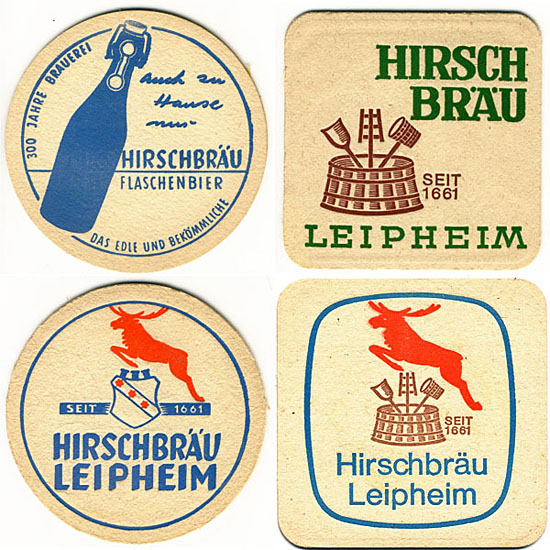
Schriftzug für Brauerei
Um welche Schriftarten handelt es sich bei diesem Schriftzug?
wenn ich mir die übergange zwischen den buchstaben
anschaue ist das keine handarbeit sonder einfach nur
runtergesetzt ...
Das sieht nicht so aus, als wären das Satzschriften, vermutlich ist das Handgezeichnet. Relativ nah dran wären Monotype Script bold und Optima.
Die Vorlage sieht so aus, als wäre sie schon mal (schlecht) per autotracing vektorisiert worden. Eventuell hilft es, den Vorgang von einer guten Vorlage ausgehend zu wiederholen.
für echte handarbeit sind zuviele unschlüssige details vorhanden.
eventuell wurde ja von hand nach einer vorlage gearbeitet und
das dann später schlecht digitalisiert ... das würde einiges erklären.
am besten man ruft bei der gaststätte an und fragt nett wer das
logo gestaltet hat und wann!
hier mal ein paar bierdeckel die ich gefunden hab.
das derzeitige logo dürfte also noch nicht sehr alt sein ...
Das kleine r ist beide Male doch sehr unterschiedlich im Detail.
mag sein das jemand das logo mit der hand gezeichnet hat -
aber sicher basierend auf einer vorlage. und diese wird gesucht!